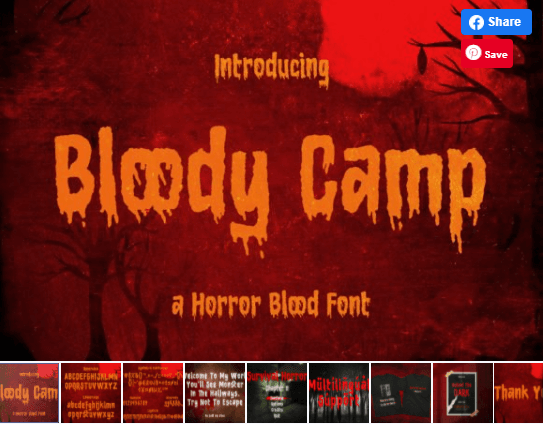
Bloody Camp Font
Bloody Camp - это креативный декоративный шрифт с плавными персонажами, создающими пугающий вид. Он подходит для проектов триллеров, приглашений на Хэллоуин, игр ужасов, жутких футболок или любых других страшных поделок!